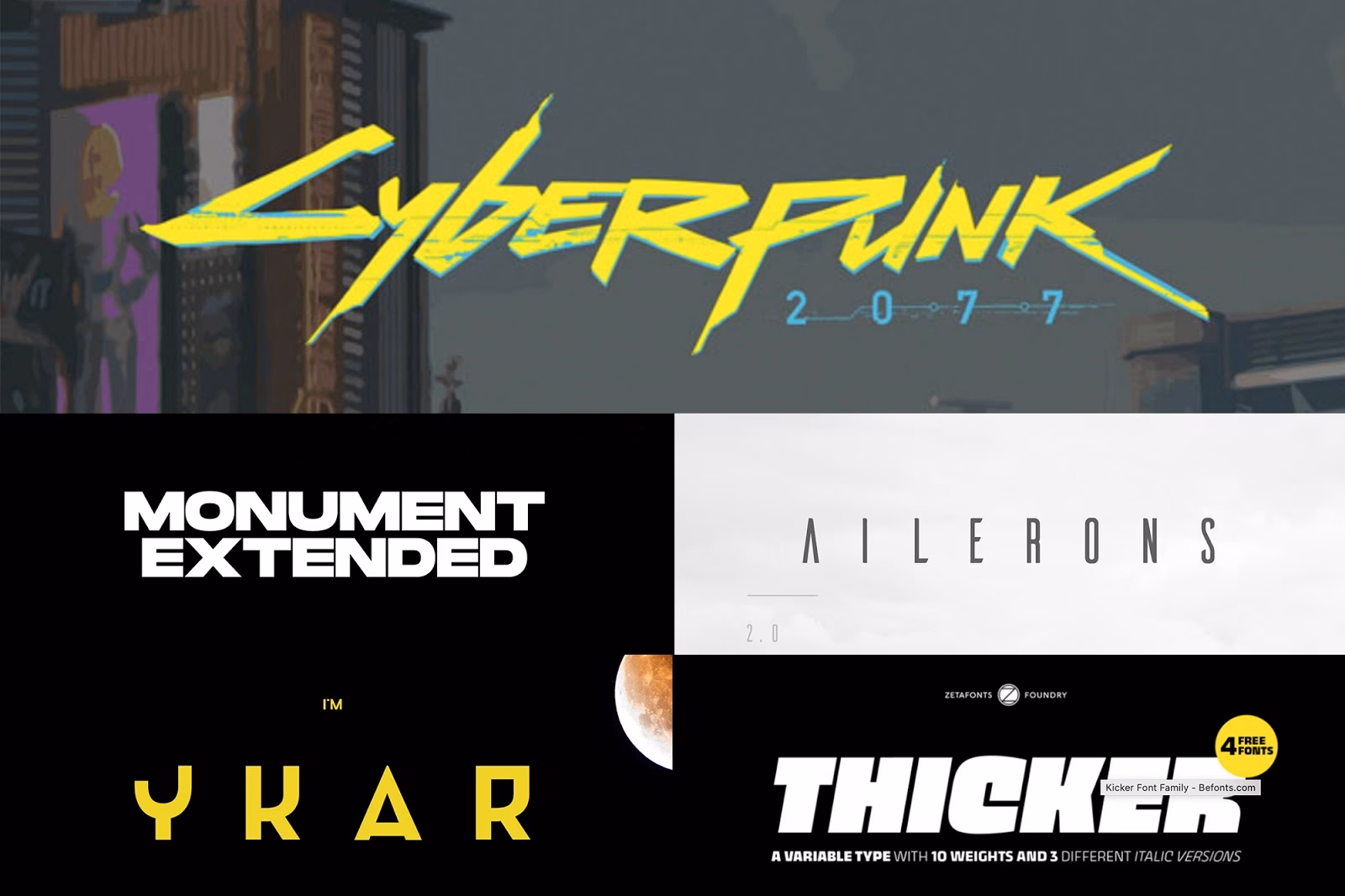
Las Mejores Fuentes de Estilo Cyberpunk
La fascinación por un futuro distópico, donde la inteligencia artificial y los cíborgs dominan un paisaje urbano bañado en luces de neón, no es algo nuevo. Desde las novelas de ciencia ficción de Isaac Asimov hasta clásicos del cine como Blade Runner, la estética cyberpunk ha impregnado el arte y el diseño durante décadas. Sin embargo, su popularidad se ha disparado recientemente, en gran parte gracias al icónico videojuego Cyberpunk 2077, que ha redefinido visualmente el género para una nueva generación. Esta tendencia ha vuelto con fuerza, y la vemos en todas partes: pósters, portadas de álbumes, diseño de productos y, por supuesto, en la web. La tipografía es un pilar fundamental de esta estética, y elegir la fuente correcta es crucial para capturar esa esencia de alta tecnología y decadencia social.
En este artículo, nos adentraremos en el neón y los circuitos para explorar las mejores fuentes de estilo cyberpunk que puedes utilizar para dar vida a tus propios diseños futuristas. Desde tipografías que emulan directamente el logo del famoso videojuego hasta opciones más sutiles y minimalistas, aquí encontrarás la herramienta perfecta para tu próximo proyecto creativo.
¿Qué Características Definen a una Fuente Cyberpunk?
Antes de sumergirnos en la lista, es importante entender qué hace que una fuente se sienta "cyberpunk". No hay una regla única, pero ciertos elementos son recurrentes y ayudan a construir esta atmósfera tan particular. Generalmente, estas tipografías comparten varias de las siguientes características:
• Formas Geométricas y Angulares: Predominan las líneas rectas, los ángulos agudos y las formas cuadradas o rectangulares, evocando circuitos, arquitectura brutalista y maquinaria avanzada.
• Efectos de "Glitch" y Distorsión: Muchas fuentes incorporan imperfecciones deliberadas, como cortes, desalineaciones o artefactos digitales, simulando un fallo en la transmisión de datos o una pantalla defectuosa.
• Estilo Stencil o Incompleto: Las letras a menudo parecen estar hechas con plantillas, con cortes en sus trazos, lo que les da un aspecto industrial y utilitario.
• Letras Anchas y Negritas: Para lograr un impacto visual fuerte, es común el uso de tipografías condensadas (altas y estrechas) o, por el contrario, muy anchas y robustas, perfectas para titulares imponentes.
• Inspiración Retro-Futurista: Un gran subgénero del cyberpunk bebe de la estética de los años 80, por lo que muchas fuentes tienen un aire retro, recordando a las primeras computadoras, videojuegos y películas de ciencia ficción de esa época.
Una Selección de Fuentes Cyberpunk para Dominar Night City
Hemos recopilado una variedad de fuentes que capturan el espíritu cyberpunk, desde las más agresivas hasta las más limpias y corporativas. A continuación, te presentamos algunas de las mejores opciones disponibles para tus proyectos.
Fuentes Inspiradas en el Juego
Para aquellos que buscan recrear la sensación directa de Cyberpunk 2077, estas opciones son el punto de partida ideal.
Cynatar: Esta es posiblemente una de las fuentes que más se acerca al estilo del logo del videojuego. Presenta letras con texturas y bordes irregulares y dentados, transmitiendo una sensación de caos y rebeldía. Es perfecta para títulos grandes y audaces que necesiten captar la atención de inmediato.
Cyberpunk (Recreación): Creada por un fan, esta fuente busca ser una réplica fiel de la tipografía del juego. Aunque no es la oficial, captura la esencia a la perfección, con sus letras angulares y su estilo inconfundible. Es ideal para proyectos de fans, carteles o cualquier diseño que busque una conexión directa con el juego.
Fuentes de Estilo Tecno y Futurista
Si buscas un look de alta tecnología pero con una identidad propia, estas tipografías son una excelente elección.
Voltec: Con un diseño de letras audaz y pesado, Voltec es fantástica para portadas de discos, miniaturas de YouTube o carteles de eventos. Incluye letras mayúsculas y minúsculas, así como una gran cantidad de caracteres alternativos y ligaduras para una mayor personalización.
Codevein: Esta fuente destaca por su singularidad. Sus caracteres únicos se alejan del aspecto cyberpunk tradicional, pero mantienen esa sensación futurista y distópica. Es una opción excelente si quieres que tus títulos se distingan del resto.
Oxta: Para quienes prefieren un enfoque más limpio y minimalista, Oxta es la elección perfecta. Ofrece un conjunto de caracteres futuristas con un diseño pulcro y bien definido. Funciona de maravilla en encabezados de sitios web, vídeos y cualquier diseño que requiera una estética moderna y sofisticada.